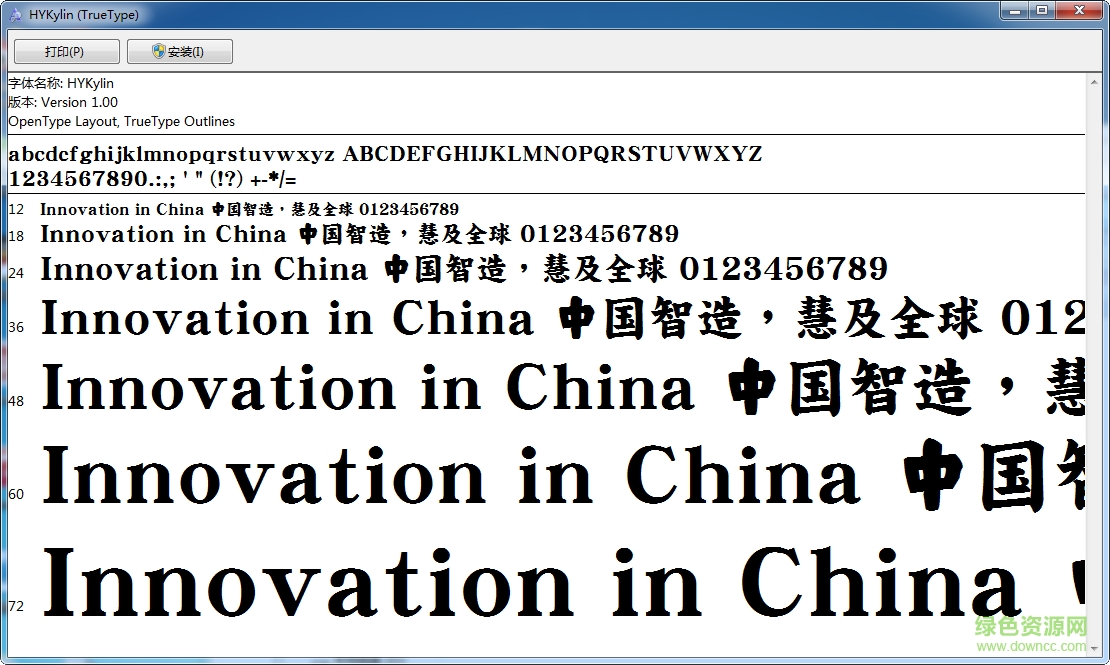
漢儀麒麟體簡繁字體包含了麒麟體簡體和繁體兩種選擇,漢儀麒麟體結(jié)構(gòu)上吸取顏楷的端莊大氣、方正樸茂,又運用疊筆勾白的表現(xiàn)手法突出筆畫間的層次關(guān)系。整體呈現(xiàn)出雄健渾厚卻又不失靈動飄逸的效果,是傳統(tǒng)藝術(shù)融入現(xiàn)代思想的和諧之作。可以應(yīng)用于廣告設(shè)計、平面設(shè)計、產(chǎn)品包裝、報刊雜志等領(lǐng)域。歡迎來綠色資源網(wǎng)下載。